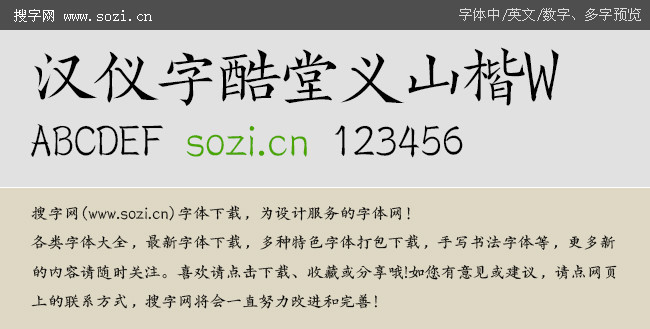
漢儀字酷堂義山楷W
搜字網(wǎng)給大家提供一款漢儀字酷堂義山楷W中文字體下載,漢儀字酷堂義山楷W字體形態(tài)清秀俊雅,能帶給人眼前一亮的舒適明朗體驗(yàn),延續(xù)了楷體字的溫文儒雅,適合應(yīng)用于書籍設(shè)計(jì)、平面海報(bào)設(shè)計(jì)、包裝設(shè)計(jì)等廣告應(yīng)用。(本字體為個(gè)人非商用版,如需要商用請(qǐng)聯(lián)系漢儀公司購(gòu)買版權(quán))